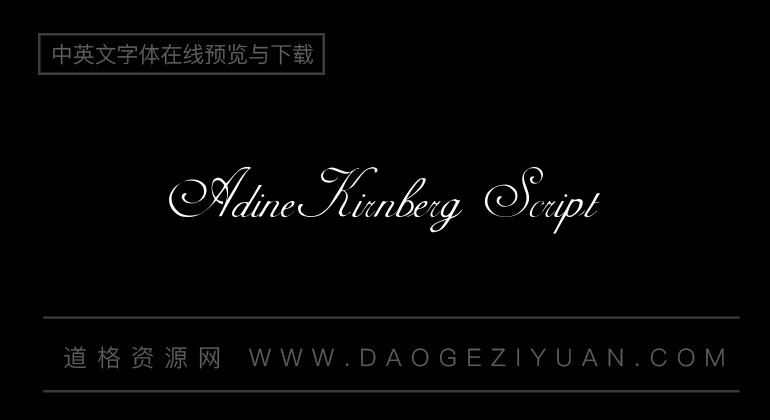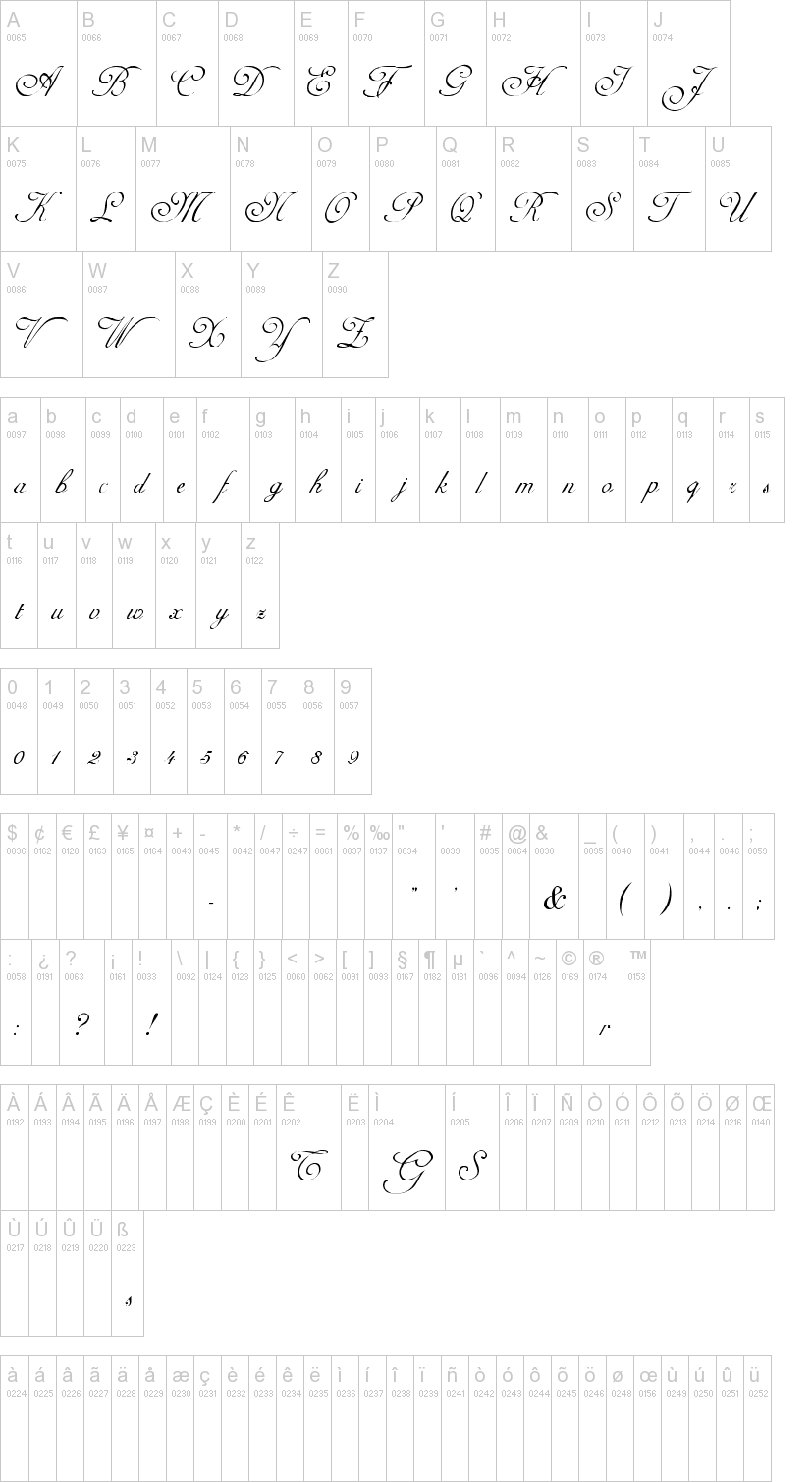
AdineKirnberg Script是一种装饰性手写字体,常用于标题、海报、传单等设计中。它的特点是笔画粗细变化大,字母之间的连接处具有流畅的曲线,并且字母有很多装饰性的花纹和细节。 这种字体的起源可以追溯到16世纪德国铸造师和书法家Johann Beringer所设计的一种装饰性字体。AdineKirnberg Script是对这种字体的现代重新设计和发展。 AdineKirnberg Script字体非常适合用于装饰性的设计,但由于字母之间的连接较多,因此在较小的字号下阅读可能会有些困难。同时,这种字体的装饰性质也使得它不适合用于正式文书、报告等需要更加简洁明了的场合。内容介绍
AdineKirnberg Script是一款非常不错的手写艺术字体,具有很好的视觉感,适合于文化类的宣传设计、商业类品牌的广告和产品包装设计以及个性化文字排版等较多场景。